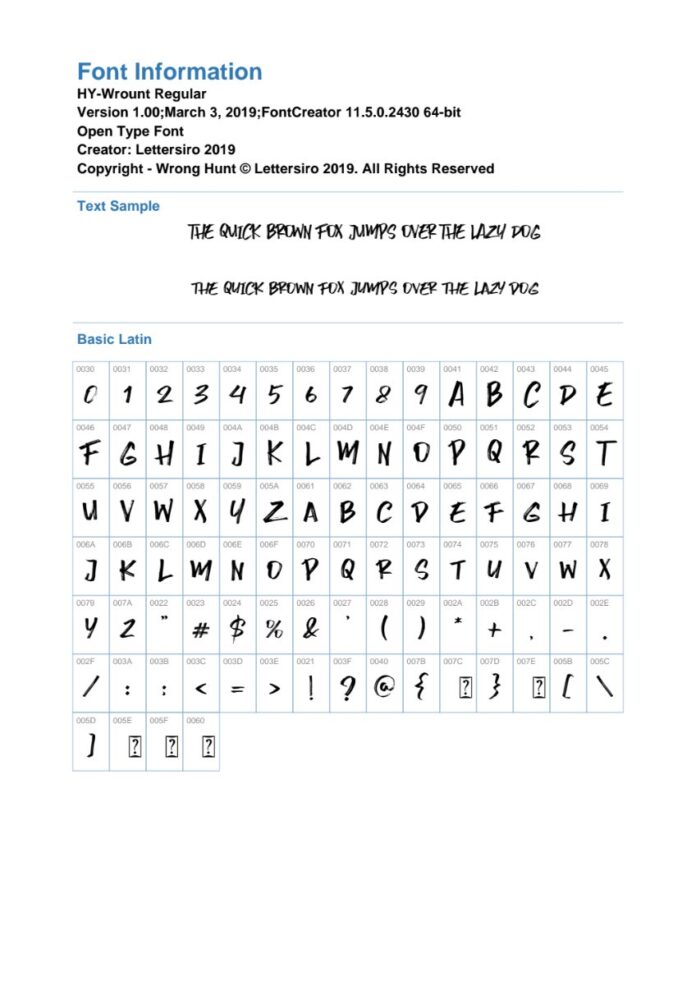
Font Chữ HY-Wrount Độc Đáo
Font HY-Wrount: Nét Chữ Viết Tay Đầy Cá Tính
HY-Wrount là một font chữ mang đậm phong cách viết tay (handwritten), nhưng không phải là kiểu thư pháp mềm mại mà là sự kết hợp giữa nét cẩu thả có chủ đích và sự mạnh mẽ, dứt khoát. Mỗi ký tự trong HY-Wrount đều toát lên vẻ tự do, phóng khoáng, như được viết bằng cọ hoặc bút lông với những nét mực đậm nhạt không đều, tạo nên một hiệu ứng rất chân thực và sống động.
Điểm đặc biệt của font này nằm ở sự không hoàn hảo có chủ ý. Các đường nét không hoàn toàn thẳng thớm, các góc cạnh có phần thô ráp, và khoảng cách giữa các chữ cái đôi khi cũng có sự biến đổi nhẹ. Chính những yếu tố này lại tạo nên vẻ đẹp riêng biệt, một sự “phá cách” đầy nghệ thuật, giúp HY-Wrount nổi bật giữa vô vàn các font chữ khác.
Đặc Điểm Nổi Bật Của Font HY-Wrount
• Phong cách viết tay độc đáo: Mô phỏng chân thực nét chữ viết tay bằng cọ hoặc bút lông, tạo cảm giác gần gũi và cá nhân.
• Mạnh mẽ và cá tính: Phù hợp cho các thiết kế muốn thể hiện sự năng động, trẻ trung, hoặc có chút nổi loạn.
• Đa dạng ký tự: Hỗ trợ đầy đủ các ký tự Latin cơ bản, số và các ký tự đặc biệt, đảm bảo tính linh hoạt trong sử dụng.
• Dễ dàng kết hợp: Dù mang phong cách mạnh mẽ, HY-Wrount vẫn có thể kết hợp hài hòa với các font chữ serif hoặc sans-serif đơn giản để tạo sự cân bằng.
Ứng Dụng Sáng Tạo Của Font HY-Wrount
Với những đặc tính nổi bật của mình, font HY-Wrount có thể được ứng dụng rộng rãi trong nhiều loại hình thiết kế khác nhau, mang lại hiệu quả thị giác cao:
1. Thiết Kế Logo và Nhận Diện Thương Hiệu
Nếu thương hiệu của bạn hướng đến sự trẻ trung, năng động, sáng tạo hoặc có chút “bụi bặm”, HY-Wrount là một lựa chọn tuyệt vời cho logo. Nó giúp tạo ra một dấu ấn riêng biệt, khó quên, thể hiện cá tính mạnh mẽ của doanh nghiệp. Ví dụ, các thương hiệu thời trang đường phố, quán cà phê nghệ thuật, hoặc studio sáng tạo có thể tận dụng font này để tạo sự khác biệt.
2. Tiêu Đề, Banner và Poster Quảng Cáo
Trong các ấn phẩm quảng cáo, tiêu đề cần phải thu hút sự chú ý ngay lập tức. HY-Wrount với những nét chữ mạnh mẽ, ấn tượng sẽ giúp tiêu đề của bạn nổi bật, dễ đọc và tạo điểm nhấn thị giác mạnh. Nó đặc biệt hiệu quả cho các sự kiện âm nhạc, festival, quảng cáo sản phẩm dành cho giới trẻ, hoặc các chương trình khuyến mãi mang tính đột phá.
3. Thiết Kế Bao Bì Sản Phẩm
Đối với các sản phẩm thủ công, sản phẩm tự nhiên, hoặc những mặt hàng muốn truyền tải câu chuyện cá nhân, font HY-Wrount có thể giúp bao bì trở nên độc đáo và gần gũi hơn. Nó tạo cảm giác sản phẩm được làm ra với sự tâm huyết và sự khác biệt.
4. Thiết Kế Áo Thun, Phụ Kiện
Những câu slogan, thông điệp in trên áo thun, mũ, túi xách khi sử dụng HY-Wrount sẽ trở nên cá tính và phong cách hơn. Nó phù hợp với những ai yêu thích phong cách streetwear, hip-hop hoặc muốn thể hiện cái tôi mạnh mẽ qua trang phục.
5. Thiết Kế Website và Ứng Dụng
Trong thiết kế giao diện người dùng, HY-Wrount có thể được sử dụng cho các tiêu đề lớn, nút bấm hoặc các yếu tố đồ họa cần tạo điểm nhấn. Tuy nhiên, cần lưu ý sử dụng một cách tiết chế để không làm giảm khả năng đọc của nội dung chính.